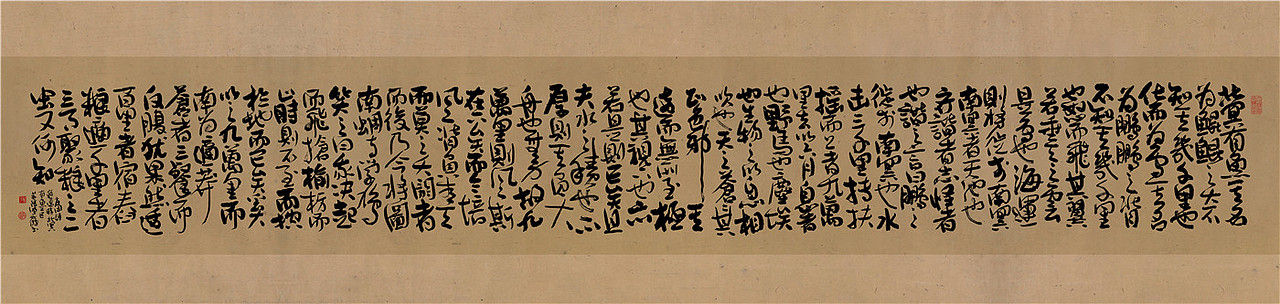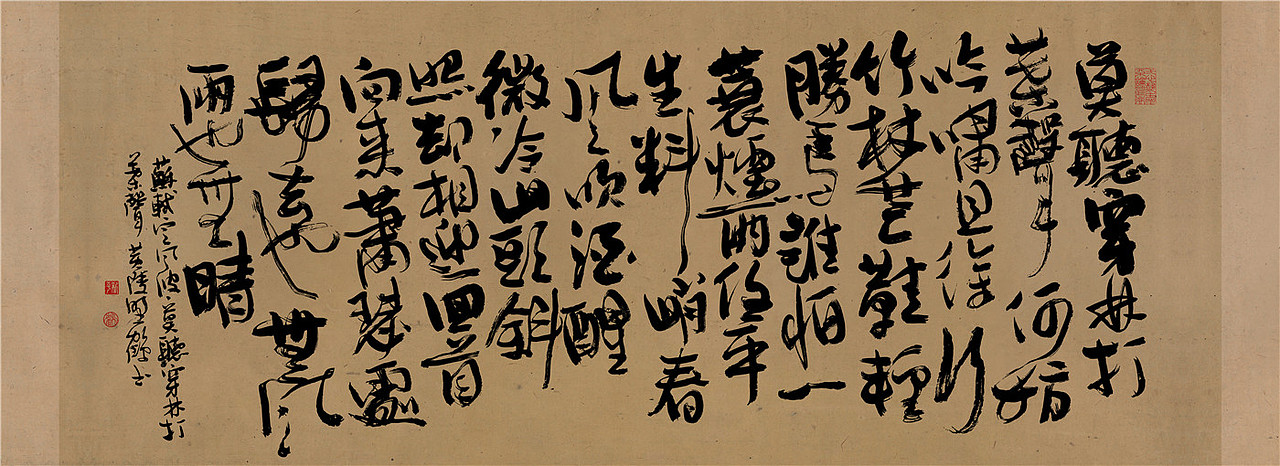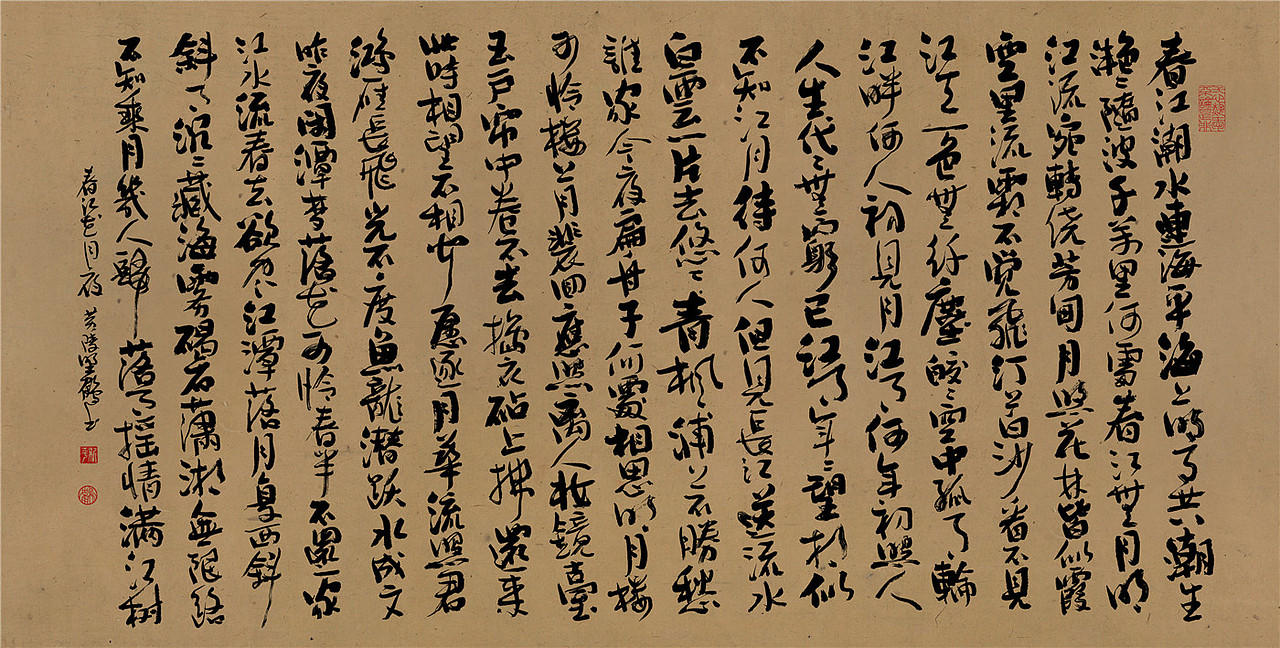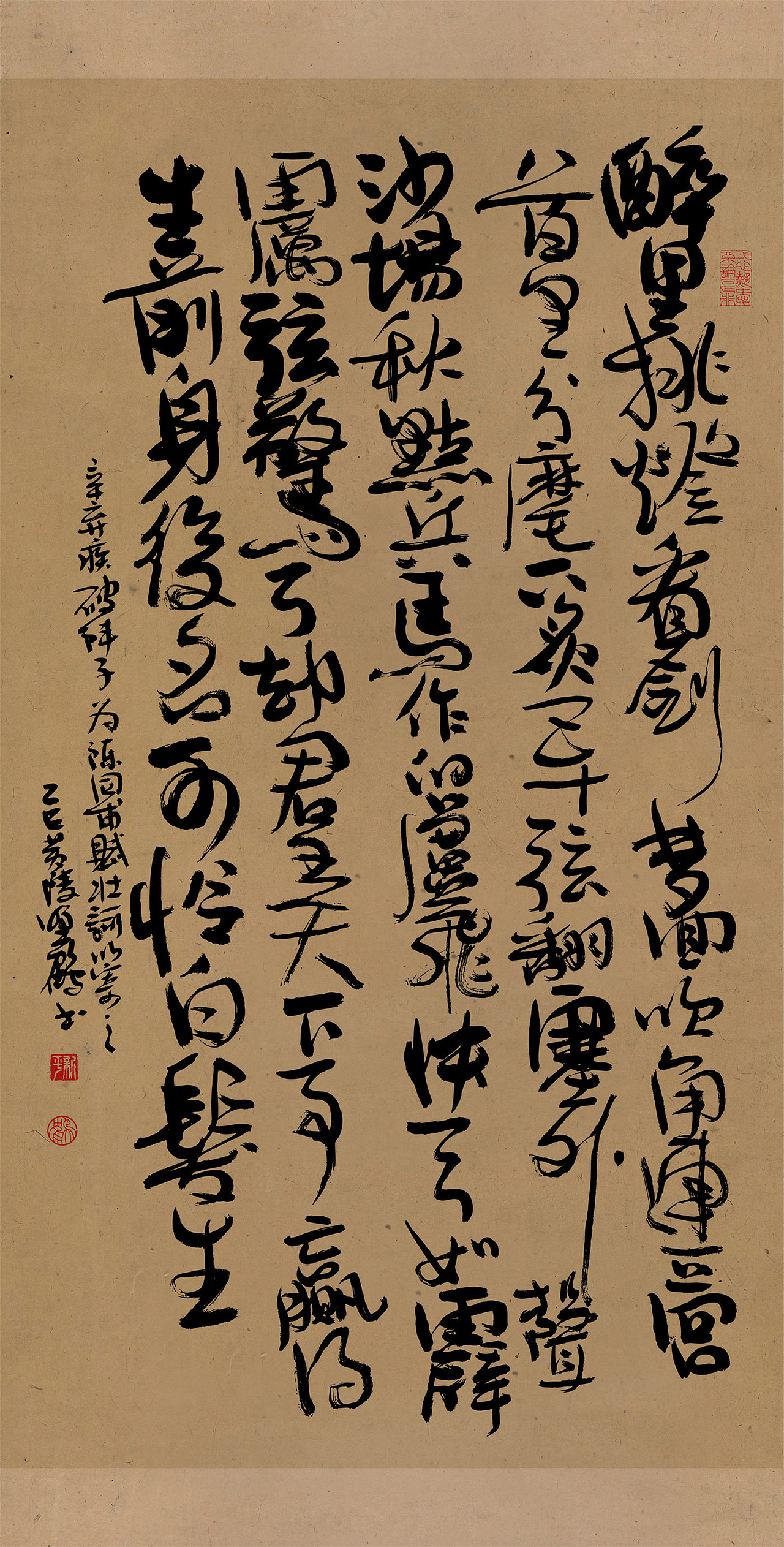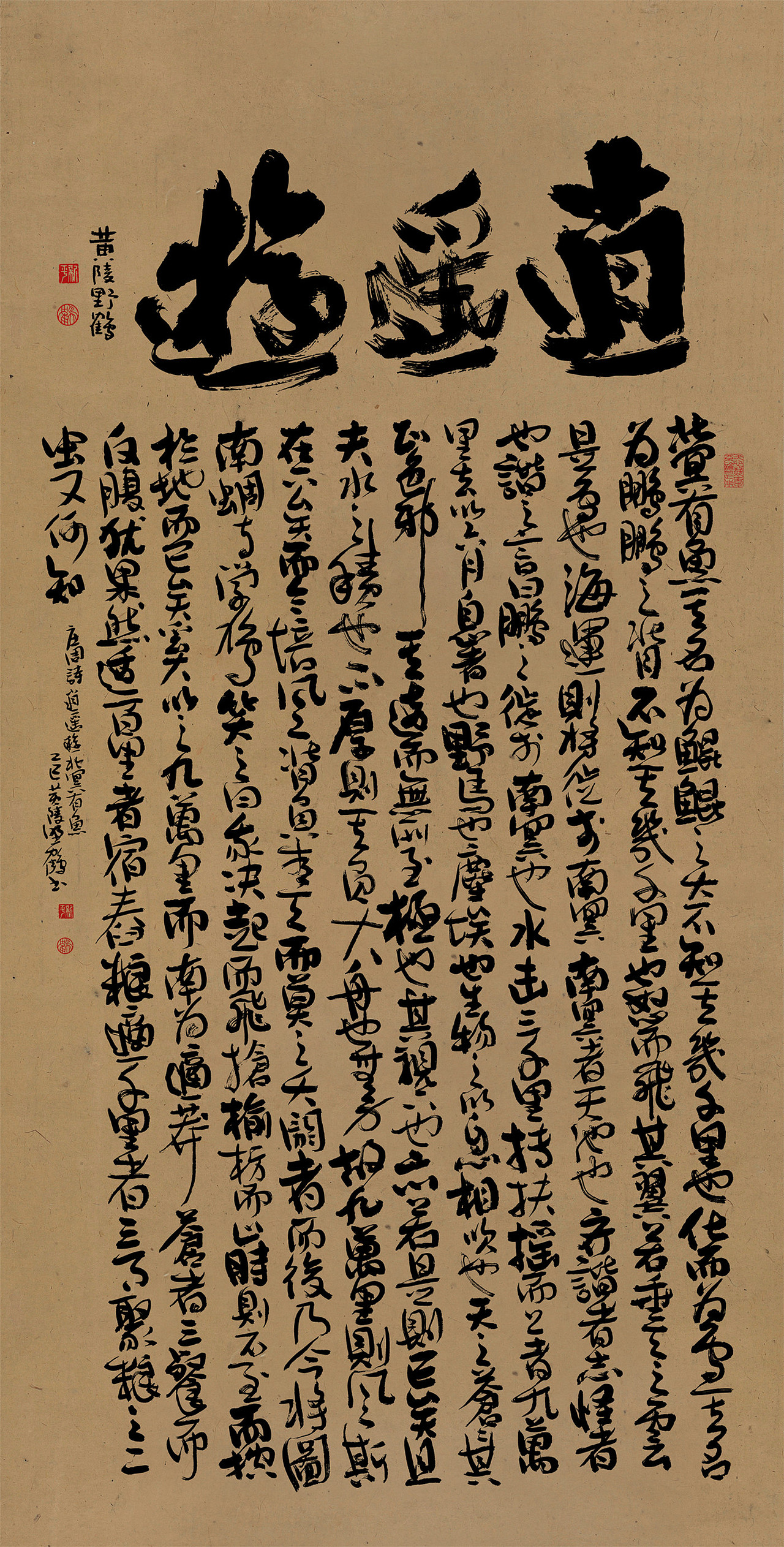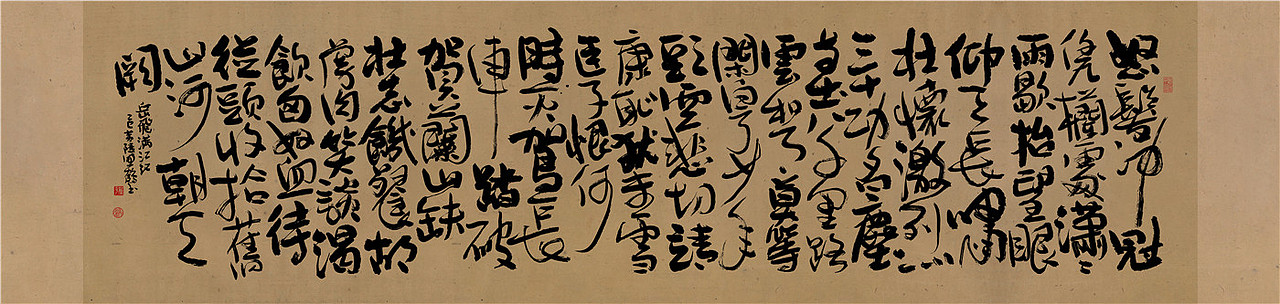
白墨研字| 黄陵野鹤-纯艺术类书法形式作品探索
是时候出一期纯艺术类的作品了:)虽然有点乱七八糟的写,但是还是挺爽的哈哈。
李白侠客行
李白飞龙引
岳飞满江红
辛弃疾破阵子
庄子逍遥游
辛弃疾破阵子
李白侠客行
辛弃疾京口北固亭怀古
李白飞龙引
岳飞满江红
李白将敬酒
杨慎临江仙
定风波
曹操观沧海
春江花月夜